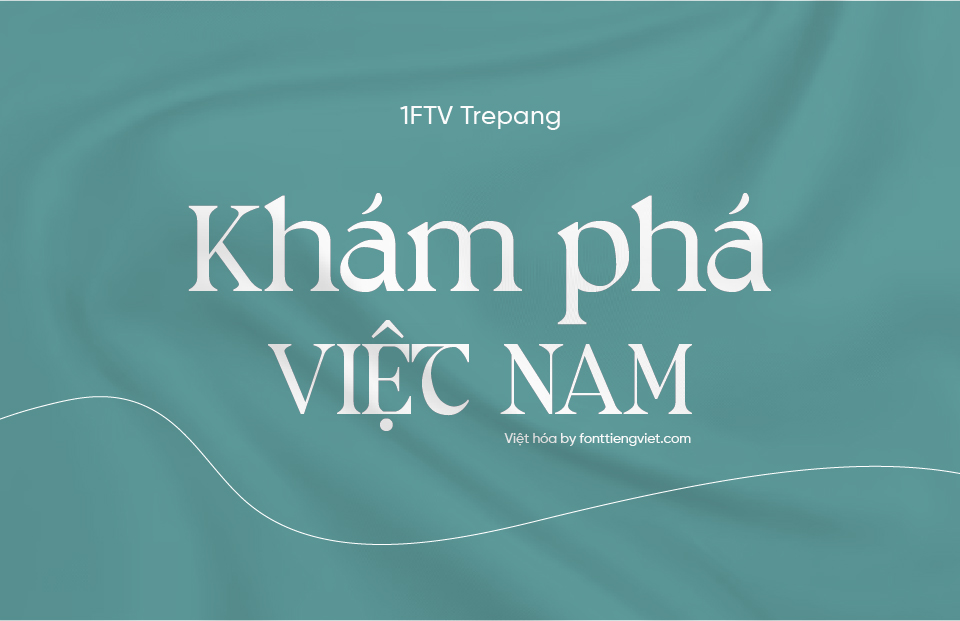
Font Việt hóa 1FTV Trepang
Giới thiệu về Font Việt hóa 1FTV Trepang
Trong thế giới đồ họa hiện đại, việc lựa chọn Font Miễn Phí phù hợp đóng vai trò then chốt giúp truyền tải thông điệp hiệu quả. Font Việt hóa 1FTV Trepang là một bộ phông chữ độc đáo, mang phong cách hiện đại và mạnh mẽ, rất phù hợp cho các bạn học sinh và giáo viên trong việc làm bài thuyết trình hoặc thiết kế báo tường. Với các đường nét dứt khoát và cấu trúc hình học tinh tế, bộ font này tạo nên sự cân bằng hoàn hảo giữa tính thẩm mỹ và khả năng đọc hiểu trên nhiều nền tảng khác nhau.
Tại sao nên sử dụng Font Việt hóa 1FTV Trepang?
Sáng tạo cùng phông chữ 1FTV Trepang